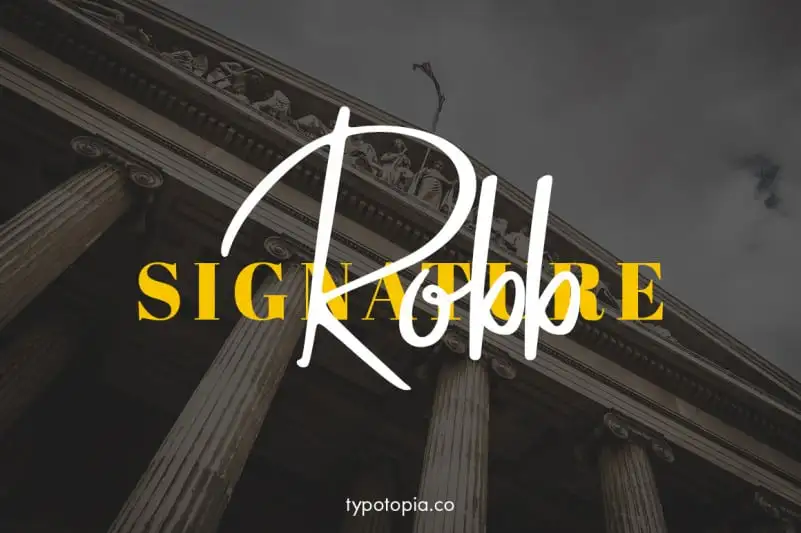
Robb Script Font – Fonte Grátis
Robb Script Font
A Robb Script Font é uma curiosa criação do typotopia, perfeitamente concebida para aqueles que buscam uma fonte escrita à mão com personalidade única e versátil. Cada caractere desta fonte foi cuidadosamente ajustado para criar um conjunto de caracteres únicos e imprimíveis, permitindo a combinação infinita de formas. A fonte é perfeita para qualquer projeto, desde editoriais até criações gráficas. Cada traço do Robb Script Font traz consigo sua própria personalidade única, fazendo com que quando os caracteres se encontram, gerem proximidades dinâmicas e agradáveis. Este design poderoso combina elegância e originalidade em um só ponto de vista, tornando-a uma fonte perfeita para qualquer situação ou projeto. A Robb Script Font é uma escolha ideal para quem busca uma fonte escrita à mão que exiba criatividade e diversão, adaptável a todos os tipos de trabalho gráfico.